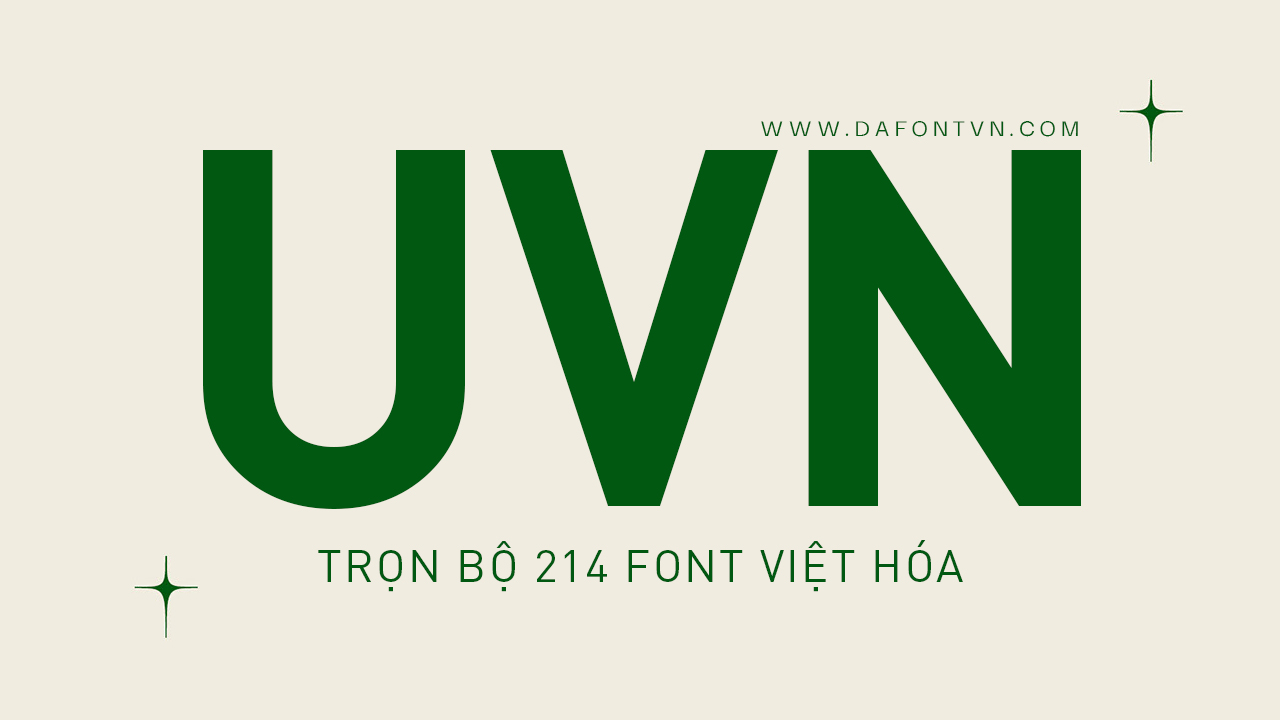
Tải trọn bộ Font UVN Việt hóa đầy đủ nhất
Bộ font UVN Việt hóa là bộ font tiếng Việt hỗ trợ bảng mã Unicode bao gồm 214 font với rất nhiều kiểu font khác nhau, phong phú đa dạng về kiểu chữ và được sử dụng rất phổ biến từ trước đến nay.
Bạn có thể sử dụng bộ font chữ này cho nhiều mục đích thiết kế khác nhau với kiểu chữ cứng cáp, mềm mại, uốn lượn hay kiểu chữ viết tay. Bộ font UVN được sử dụng khá thông dụng như soạn thảo văn bản, thiết kế đồ họa, quảng cáo…